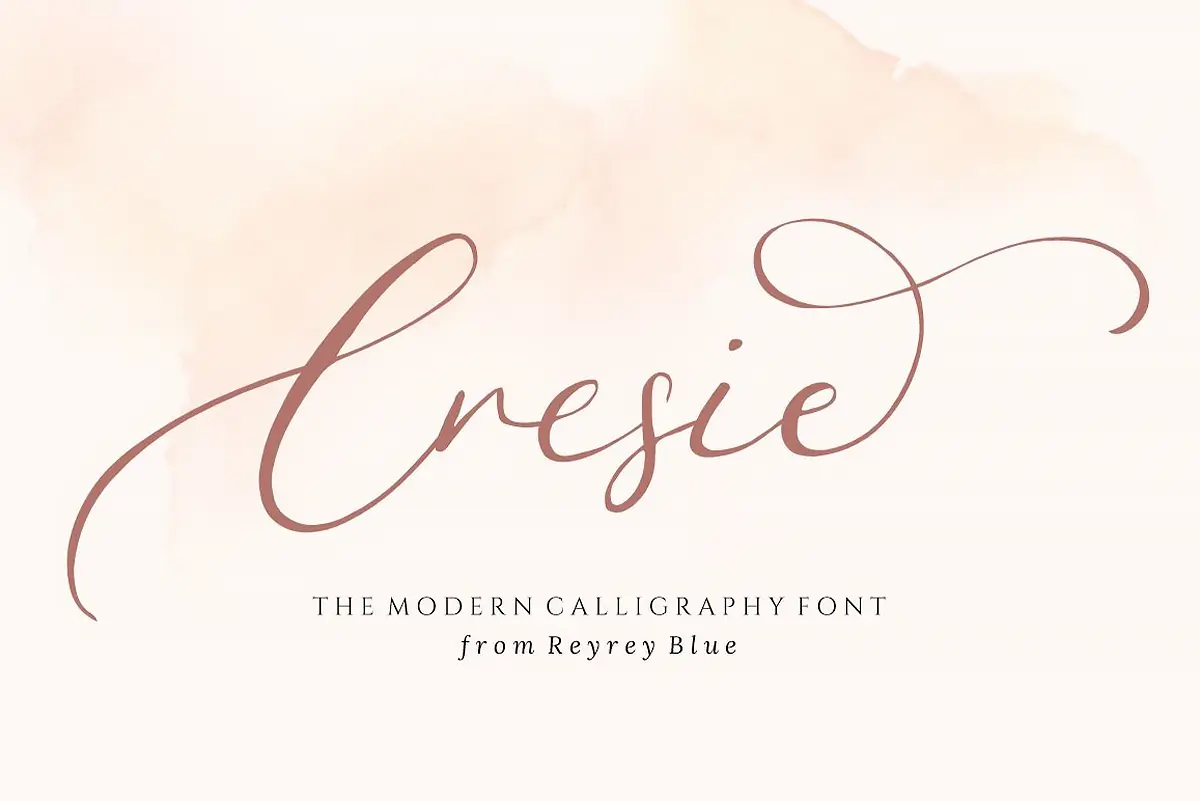
فونت عاشقانه و رمانتیک رایگان
فونت Cresie یک فونت دست نویس زیبا و ماندگار است که برای طراحی‌های مدرن و خلاقانه انتخابی عالی محسوب می‌شود. هر کاراکتر این فونت با لمس منحصربه‌فرد و ظریف طراحی شده تا به طرح‌های شما روح و شخصیت ببخشد. این فونت برای لوگوها، برندینگ، نقل‌قول‌ها و طراحی‌های تبلیغاتی بسیار مناسب است.
⭐ ویژگی‌های محصول:
• سبک دست‌نویس مدرن و زیبا
• مناسب برای طراحی لوگو، برندینگ و نقل‌قول‌های چشم‌نواز
• هر کاراکتر با جزئیات منحصربه‌فرد طراحی شده
• فونتی تمیز، خوانا و حرفه‌ای
🎯 موارد استفاده:
• طراحی لوگوهای خلاقانه و شخصی‌سازی‌شده
• پروژه‌های برندینگ و هویت بصری
• کارت‌های دعوت و استیشنری
• نقل‌قول‌های تایپوگرافی و پوسترهای هنری
• پست‌های شبکه‌های اجتماعی با جلوه دست‌نویس